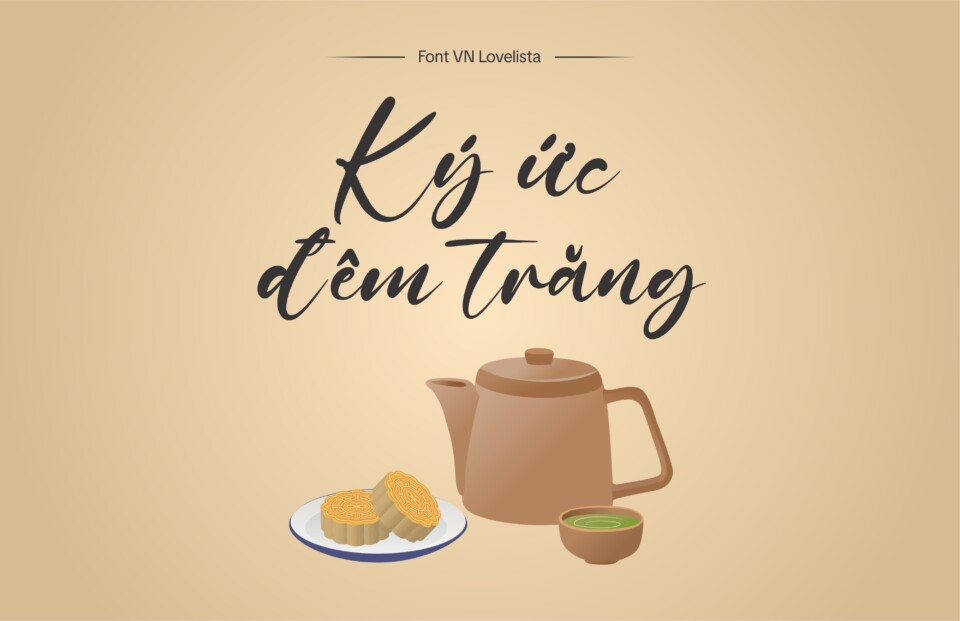
Trong thế giới thiết kế đồ họa rộng lớn, việc lựa chọn một Font Chữ phù hợp có vai trò cực kỳ quan trọng, quyết định đến thẩm mỹ và thông điệp mà bạn muốn truyền tải. Và trong số vô vàn lựa chọn, Font Việt hóa VN Lovelista nổi lên như một làn gió mới, mang đến vẻ đẹp tinh tế, bay bổng và đầy cảm xúc. Được nhiều nhà thiết kế ưa chuộng, VN Lovelista không chỉ là một phông chữ đẹp mắt mà còn là công cụ đắc lực giúp nâng tầm các dự án sáng tạo của bạn, từ thiệp mời, logo cho đến các ấn phẩm truyền thông đa dạng. Cùng khám phá sâu hơn về sức hút đặc biệt của font chữ này và cách nó có thể biến hóa các tác phẩm của bạn trở nên độc đáo và thu hút hơn.
Tại Sao Font Việt hóa VN Lovelista Lại Được Ưa Chuộng Đến Vậy?
Font Việt hóa VN Lovelista là một kiểu chữ script (chữ viết tay) với những nét uốn lượn mềm mại, uyển chuyển, gợi lên sự lãng mạn và thanh lịch. Sự kết hợp giữa phong cách cổ điển và hơi thở hiện đại đã tạo nên một vẻ đẹp độc đáo, khó lẫn. Điều đặc biệt khiến font này trở thành lựa chọn hàng đầu cho các nhà thiết kế Việt Nam chính là khả năng Việt hóa hoàn hảo. Mọi dấu câu, ký tự đặc biệt trong tiếng Việt đều được xử lý tinh tế, đảm bảo tính thẩm mỹ và dễ đọc, không gặp phải lỗi hiển thị hay mất nét thường thấy ở các font nước ngoài chưa được Việt hóa.
Đặc Điểm Nổi Bật Của VN Lovelista
Một trong những điểm mạnh của VN Lovelista là sự đa dạng trong cách biểu cảm. Dù mang phong cách viết tay, font vẫn giữ được sự rõ ràng, dễ đọc, phù hợp cho nhiều mục đích sử dụng. Các ký tự được thiết kế với độ cong mềm mại, độ dày nét vừa phải, tạo cảm giác nhẹ nhàng nhưng vẫn đủ ấn tượng. Điều này đặc biệt quan trọng trong các thiết kế cần sự tinh tế như thiệp cưới, bao bì sản phẩm cao cấp hay các ấn phẩm mang tính cá nhân hóa. Font chữ này còn thể hiện sự linh hoạt đáng kinh ngạc khi có thể kết hợp hài hòa với nhiều loại font serif hoặc sans-serif khác, tạo ra những bố cục typographic cân đối và thu hút.
Không chỉ dừng lại ở mặt thẩm mỹ, Font Việt hóa VN Lovelista còn tối ưu hóa trải nghiệm người dùng. Với phiên bản Việt hóa chất lượng cao, người dùng không còn lo lắng về việc phải điều chỉnh từng ký tự hay gặp phải các lỗi hiển thị gây mất thời gian và công sức. Mọi thứ đã được chuẩn bị sẵn sàng, giúp bạn tập trung hoàn toàn vào ý tưởng và sự sáng tạo của mình. Đây là một lợi thế lớn, đặc biệt đối với học sinh, sinh viên hay những người mới bắt đầu học thiết kế, muốn tạo ra những sản phẩm chuyên nghiệp mà không cần quá nhiều kinh nghiệm về typography phức tạp.
Ứng Dụng Đa Dạng Của Font Việt hóa VN Lovelista Trong Thiết Kế
Với vẻ đẹp độc đáo và khả năng Việt hóa hoàn chỉnh, VN Lovelista mở ra cánh cửa cho vô vàn ứng dụng sáng tạo. Bạn có thể dễ dàng bắt gặp font chữ này trong nhiều lĩnh vực khác nhau, từ thiết kế cá nhân đến các dự án thương mại lớn.
- Thiệp cưới và thiệp mời: Nét chữ bay bổng, lãng mạn của VN Lovelista rất phù hợp để tạo ra những tấm thiệp cưới, thiệp mời sự kiện sang trọng và ý nghĩa, để lại ấn tượng khó phai trong lòng khách mời.
- Thiết kế logo và nhận diện thương hiệu: Đối với các thương hiệu muốn xây dựng hình ảnh nữ tính, thanh lịch, hoặc mang đậm tính cá nhân, VN Lovelista là một lựa chọn tuyệt vời. Nó giúp tạo ra logo độc đáo, dễ nhận diện và truyền tải được tinh thần của thương hiệu.
- Poster, banner và ấn phẩm quảng cáo: Dù là chữ viết tay, nhưng VN Lovelista vẫn đảm bảo tính dễ đọc khi được sử dụng trong các tiêu đề lớn, giúp thu hút sự chú ý của người xem một cách hiệu quả.
- Bao bì sản phẩm: Font chữ này có thể làm tăng thêm vẻ cao cấp, tinh tế cho bao bì sản phẩm, đặc biệt là các mặt hàng thủ công, mỹ phẩm hay thực phẩm có giá trị thẩm mỹ cao.
- Sách, tạp chí và báo cáo: Trong một số trường hợp, VN Lovelista có thể được sử dụng cho các tiêu đề phụ hoặc điểm nhấn văn bản, mang lại sự tươi mới và độc đáo cho bố cục tổng thể.
- Bài tập, dự án học tập: Học sinh, sinh viên có thể dùng font này để làm cho các bài thuyết trình, báo cáo hay bìa sách thêm phần sinh động và sáng tạo, thể hiện cá tính riêng.
Sự linh hoạt này giúp Font Việt hóa VN Lovelista trở thành một “vũ khí bí mật” trong bộ sưu tập font của mọi nhà thiết kế, từ chuyên nghiệp đến nghiệp dư, từ học sinh trung học chuẩn bị dự án tốt nghiệp đến sinh viên đại học làm luận văn.
Khi sử dụng, hãy cân nhắc kết hợp VN Lovelista với các font chữ khác. Do VN Lovelista có đặc trưng riêng, việc pairing với một font sans-serif hoặc serif đơn giản, dễ đọc sẽ tạo nên sự cân bằng, giúp nội dung không bị rối mắt. Ví dụ, bạn có thể dùng VN Lovelista cho tiêu đề và một font sans-serif cơ bản cho phần nội dung chính. Hãy thử nghiệm với các kích cỡ, khoảng cách chữ (kerning) và màu sắc khác nhau để tìm ra sự kết hợp ưng ý nhất cho dự án của mình.
Ngoài ra, đừng ngại khám phá các biến thể hoặc phong cách khác nhau nếu font có sẵn. Một số font Việt hóa có thể đi kèm với các ký tự thay thế (alternates) hoặc swashes, giúp bạn thêm vào những điểm nhấn độc đáo, cá nhân hóa thiết kế mà không làm mất đi tính nhất quán tổng thể. Việc này đặc biệt hữu ích cho các dự án yêu cầu sự sáng tạo và độc đáo cao, như thiết kế các ấn phẩm nghệ thuật hay thương hiệu cá nhân.